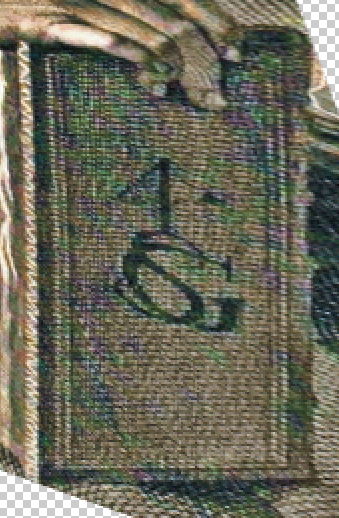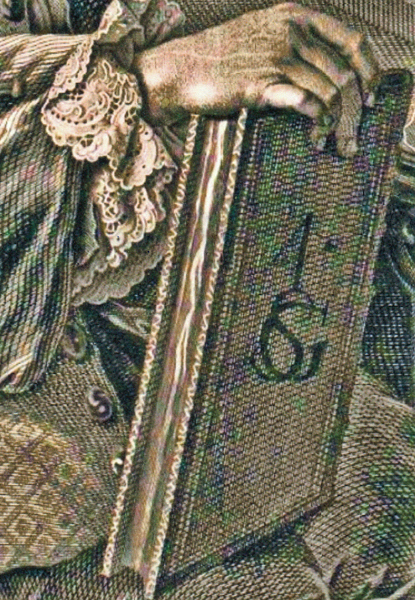
heute brauche ich Hilfe von den historisch Bewanderten. Es geht um die historisch möglichst richtige Rekonstruktion eines alten Gildezeichens (um 1700 bis 1800, Niederschlesien), was aber nur auf einem Kupferstich zu sehen ist. Dort erscheint es auf einem schräg stehenden Buchdeckel. Die Zeichen 4, S und G sind dort ineinander verwoben.
Das Problem:
Die Rekonstruktion gelingt mir nicht, weil der Kupferstecher die Perspektive nicht richtig wiedergegeben hat. Setzt man die 4 gerade ist der Rest total verzerrt. Man sieht schon auf dem Original, dass sich S und G nicht auf die Ebene des Buchdeckels legen. Obendrein liegt die Vorlage in miserabler Qualität vor.
Also: neu machen.
Nun ergeben sich mir mehrere Fragen:
1) Mit welcher Schrift solte man hier zu Werke gehen?
2) Ist die Form des "G" nicht völlig untypisch, mit der dünnen Serife oben und dem dicken Aufstrich samt dicker Serife unten?
3) Ist die geschwungene Form des "S" ganz ohne Serifen nicht auch ganz untypisch?
4) Ist das am Ende des Querstriches bei der "4" eine "Monster-Serife fern ab der Heimat" oder Mückendreck?
Ist das überhaupt eine 4? Könnte auch eine 1 und ein Є sein …
Du hast Recht, es ist wahrscheinlich gar keine 4. Aber eine 1 und ein Є sehe ich nicht. Wahrscheinlich geht es mehr in die Richtung der Grafik hier. Ich habe leider keine Ahnung von diesen alten Zeichen.
Nachdem S und G schief sind, könnte die 4 aber auch ein A sein.
Ich denke bei einem solchen Zeichen zuallererst an ein Monogramm eines Kupferstechers und habe deshalb bei Nagler, Monogrammisten nachgesehen und dort prompt ein ähnliches Zeichen gefunden. Es ist zu sehen bei
http://digital.ub.uni-duesseldorf.de/ihd/content/pageview/1402308 in der Mitte der Seite, Nr. 4099
und stellt die Druckermarke des Jenaer Druckers Georg Senzenwald dar. Da in der Graphik das Zeichen auf einem Buch dargestellt ist, denke ich dass damit das Rätsel gelöst ist.
Es sollte sich entweder um eine Zeichen der Steinmetze handeln oder um eines der Tuchhändler in Hirschberg, Niederschlesien. Man datiert den Kupferszich auf die Mitte des 18. Jahrhunderts.
Da es sich um die Zuarbeit für einen Historiker handelt, bleiben mir nur durch das Bild zu viele Fragen offen.